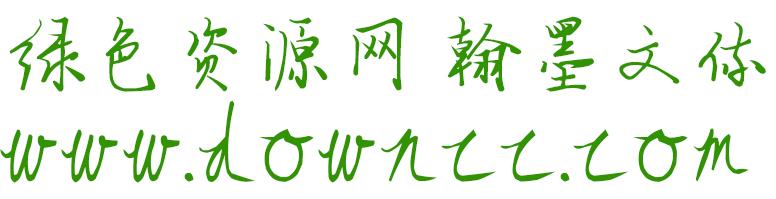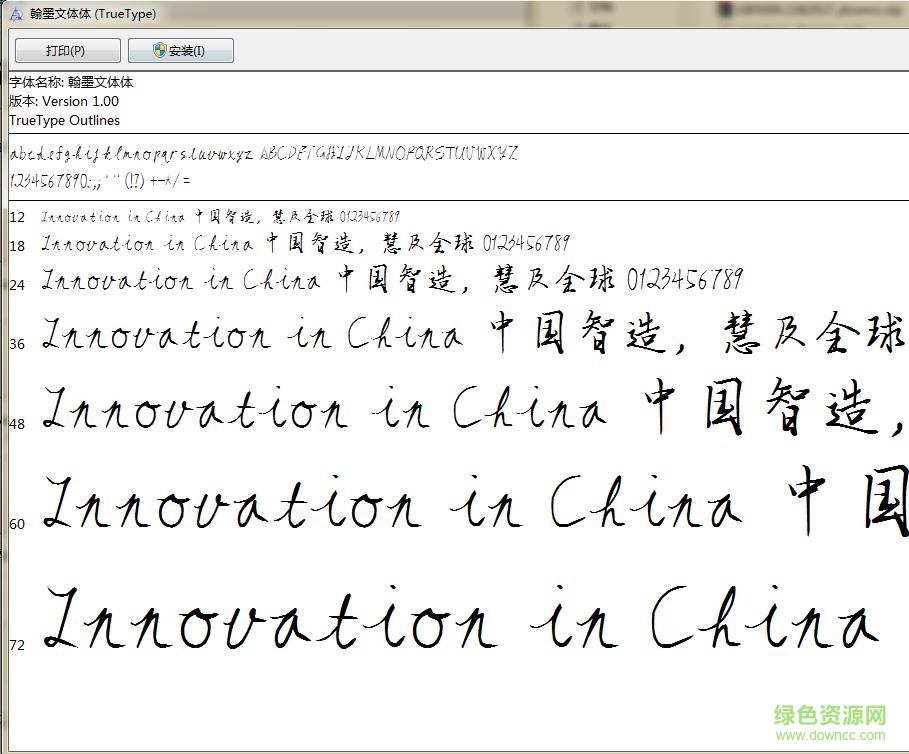
翰墨文體ttf這款字體一入眼就有一種十分不錯的文學(xué)氣息撲面而來,字體結(jié)構(gòu)十分流暢,擁有一種隨性的美感,更是提現(xiàn)出一種集大成的文學(xué)氣息,快來綠色資源網(wǎng)下載吧!
翰墨文體體在使用的時候可以運用到很多的山水畫卷中,在中國風(fēng)的動漫,或者動畫中都能夠帶來很好的顯示效果,而且在日常的文字輸入過程中也能夠帶給你美感,更多字體可以在綠色資源網(wǎng)留言獲取哦!